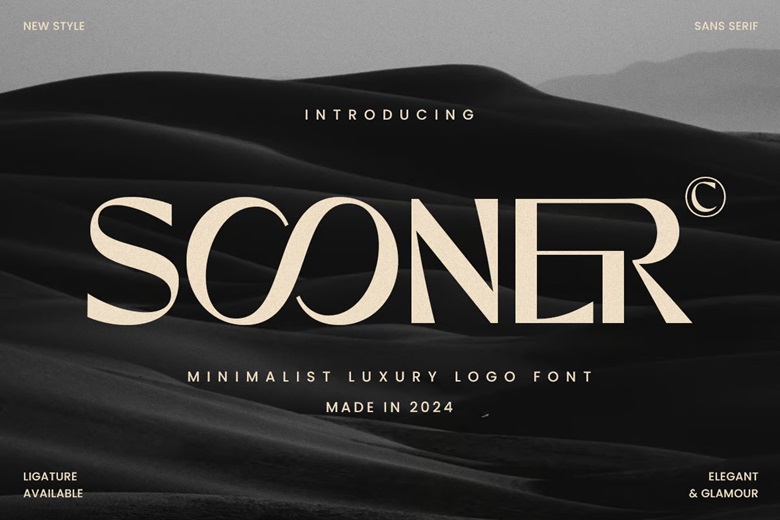
Font Sooner đẹp dành cho thiết kế
Font Sooner là một font chữ script viết tay hiện đại, nổi bật với đường nét uyển chuyển, mềm mại và đậm chất cá nhân. Kiểu chữ này được thiết kế theo phong cách hand-lettering (chữ vẽ tay), rất lý tưởng để tạo điểm nhấn lãng mạn, thanh lịch trong các thiết kế.
Đặc điểm nổi bật của Font Sooner
• Nét chữ viết tay mềm mại: Được mô phỏng từ nét viết tay tự nhiên, Sooner mang lại cảm giác gần gũi, tình cảm, rất thích hợp cho các thiết kế mang tính cá nhân hoặc thủ công.
• Kết cấu mảnh mai, uyển chuyển: Nét chữ có độ nghiêng nhẹ, không quá cầu kỳ nhưng vẫn rất duyên dáng, thể hiện sự tinh tế và dịu dàng.
• Ký tự liền mạch (ligatures): Các chữ cái được kết nối mềm mại với nhau, tạo sự liên tục và hài hòa phù hợp cho những đoạn văn ngắn như tiêu đề, trích dẫn.
• Việt hóa đẹp: Font đã được việt hóa hoàn chỉnh, các dấu tiếng Việt được bố trí hợp lý, đảm bảo không bị vỡ hoặc mất cân đối.
Ứng dụng của Font Sooner
Với vẻ ngoài nhẹ nhàng và nghệ thuật, Sooner thường được dùng trong các dự án thiết kế mang phong cách nữ tính, tình cảm hoặc cá nhân hóa, như:
• Thiệp cưới, thiệp mời, thiệp chúc mừng: Font mang lại cảm giác nhẹ nhàng, lãng mạn rất phù hợp với các dịp đặc biệt.
• Trích dẫn truyền cảm hứng, typography nghệ thuật: Thể hiện những câu nói ý nghĩa với kiểu chữ viết tay đầy cảm xúc.
• Thiết kế logo, bao bì mỹ phẩm, thời trang nữ: Tăng độ nữ tính và duyên dáng cho thương hiệu.
• Blog, mạng xã hội, tiêu đề nội dung cá nhân: Tạo cảm giác thân thiện, gần gũi và chân thực.
Font Sooner là lựa chọn hoàn hảo cho những ai đang tìm kiếm một font chữ viết tay thanh thoát, hiện đại và đầy tính thẩm mỹ. Với sự mềm mại nhưng rõ ràng, Sooner giúp bạn dễ dàng tạo ra những thiết kế đậm chất cá nhân, lãng mạn và nghệ thuật – dù là trong thiệp cưới hay bài đăng mạng xã hội.